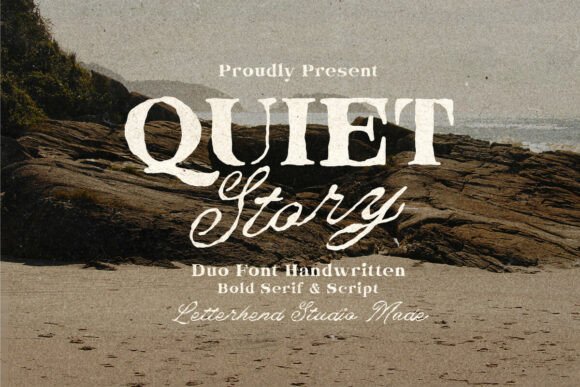
Quiet Story
適切なデザイン要素を見つけるのは難しい場合がありますが、Quiet Storyは作品を即座に引き立てる優れたコレクションを提供します。
POD(オンデマンド印刷)製品、結婚式の招待状、またはソーシャルメディアのグラフィックを作成している場合でも、Quiet Storyは理想的です。